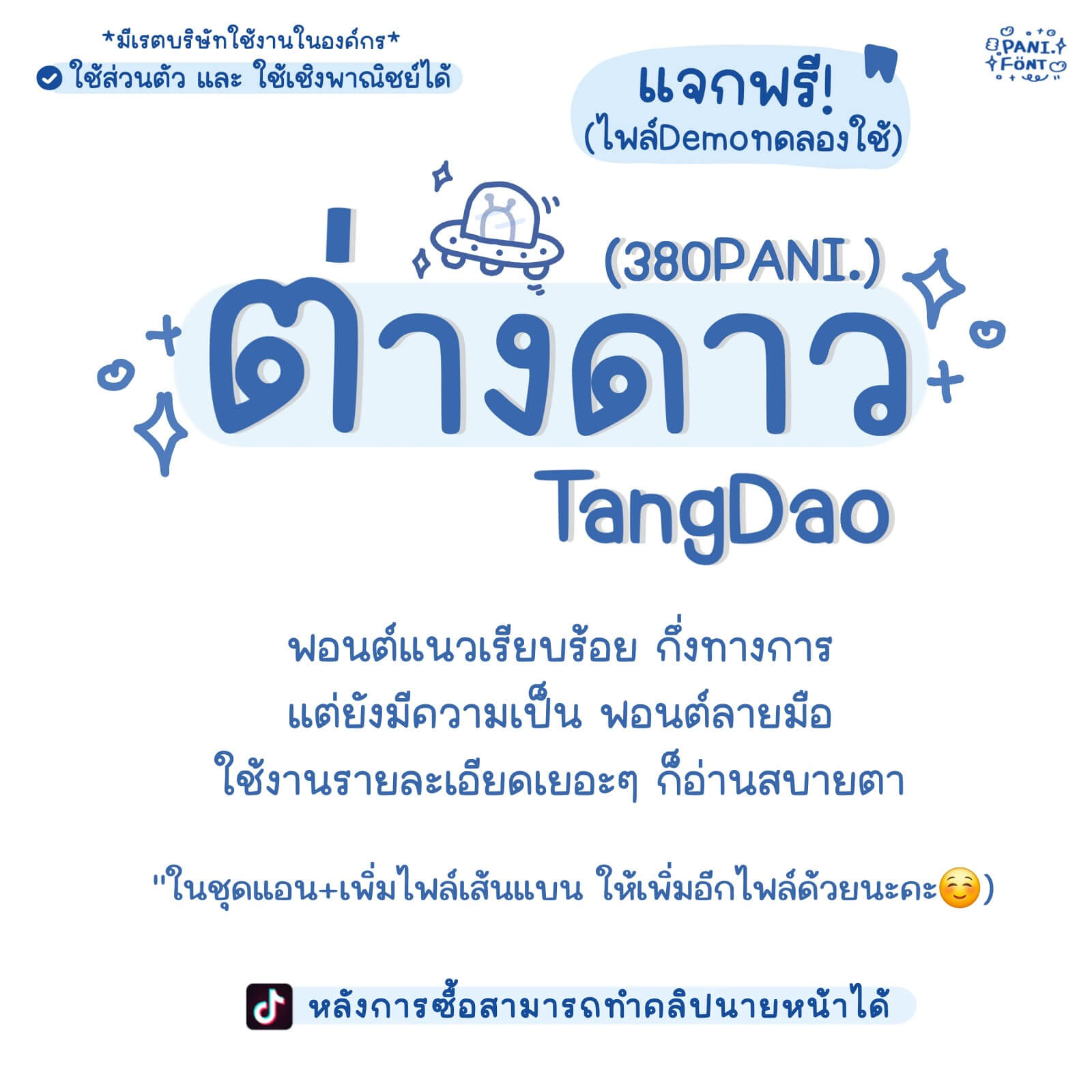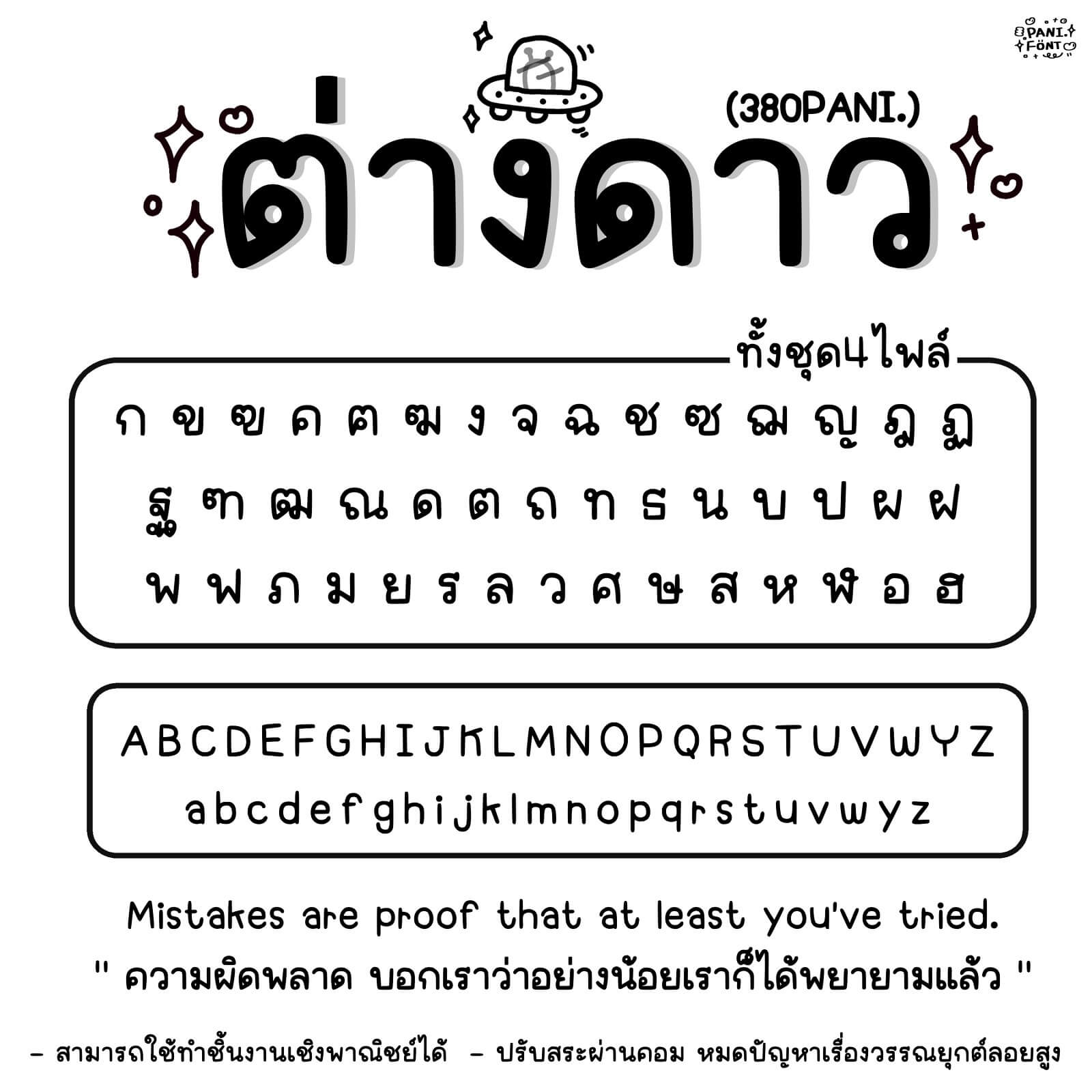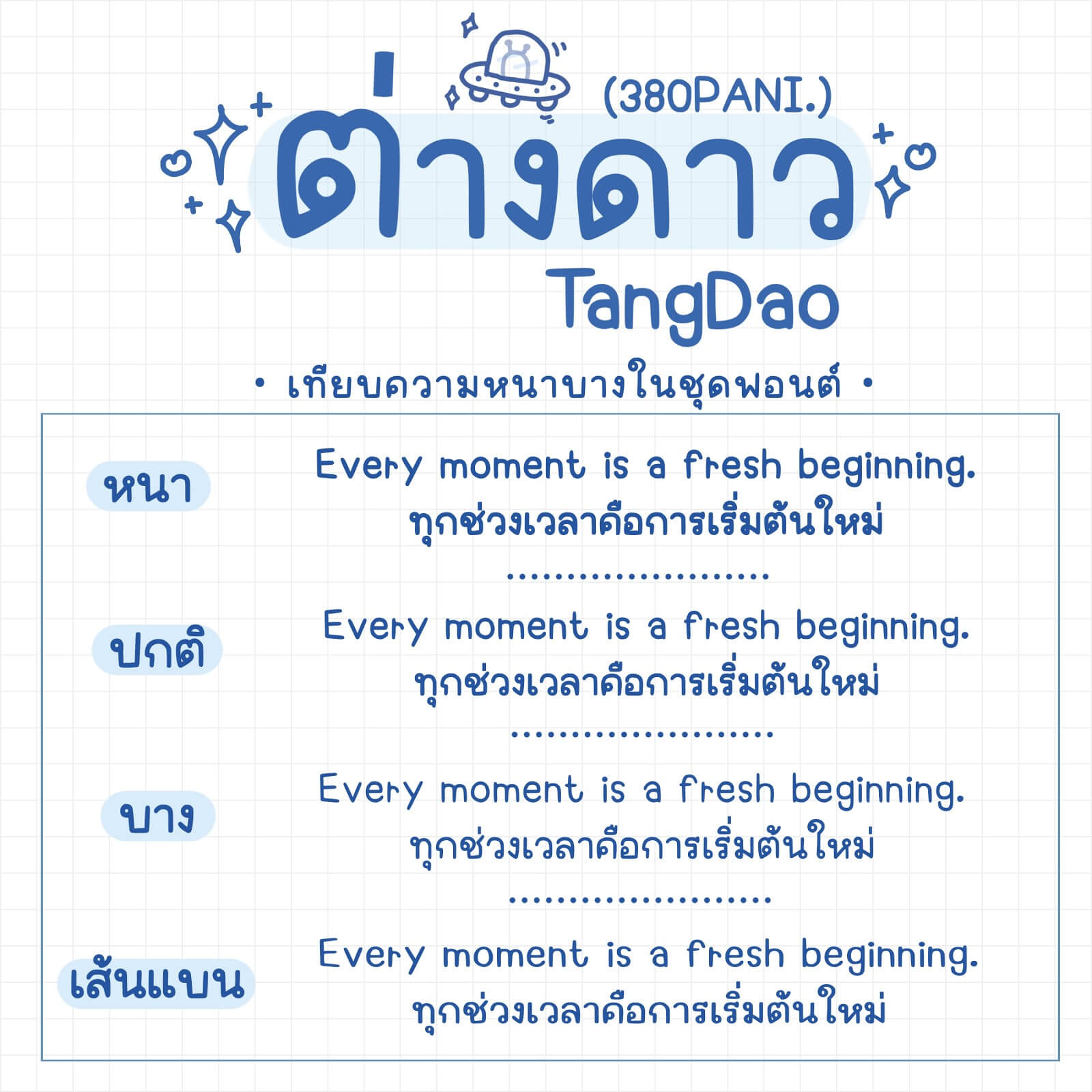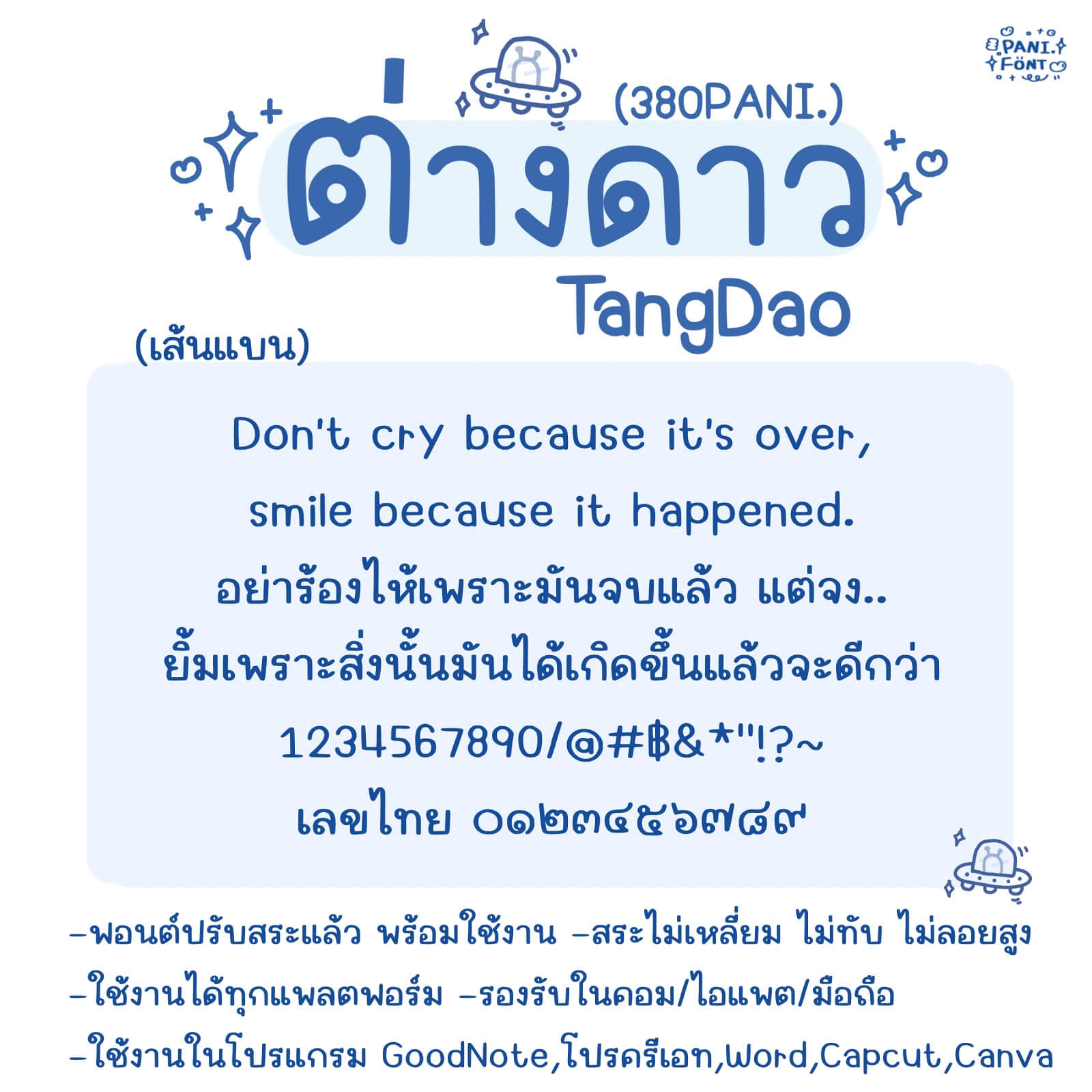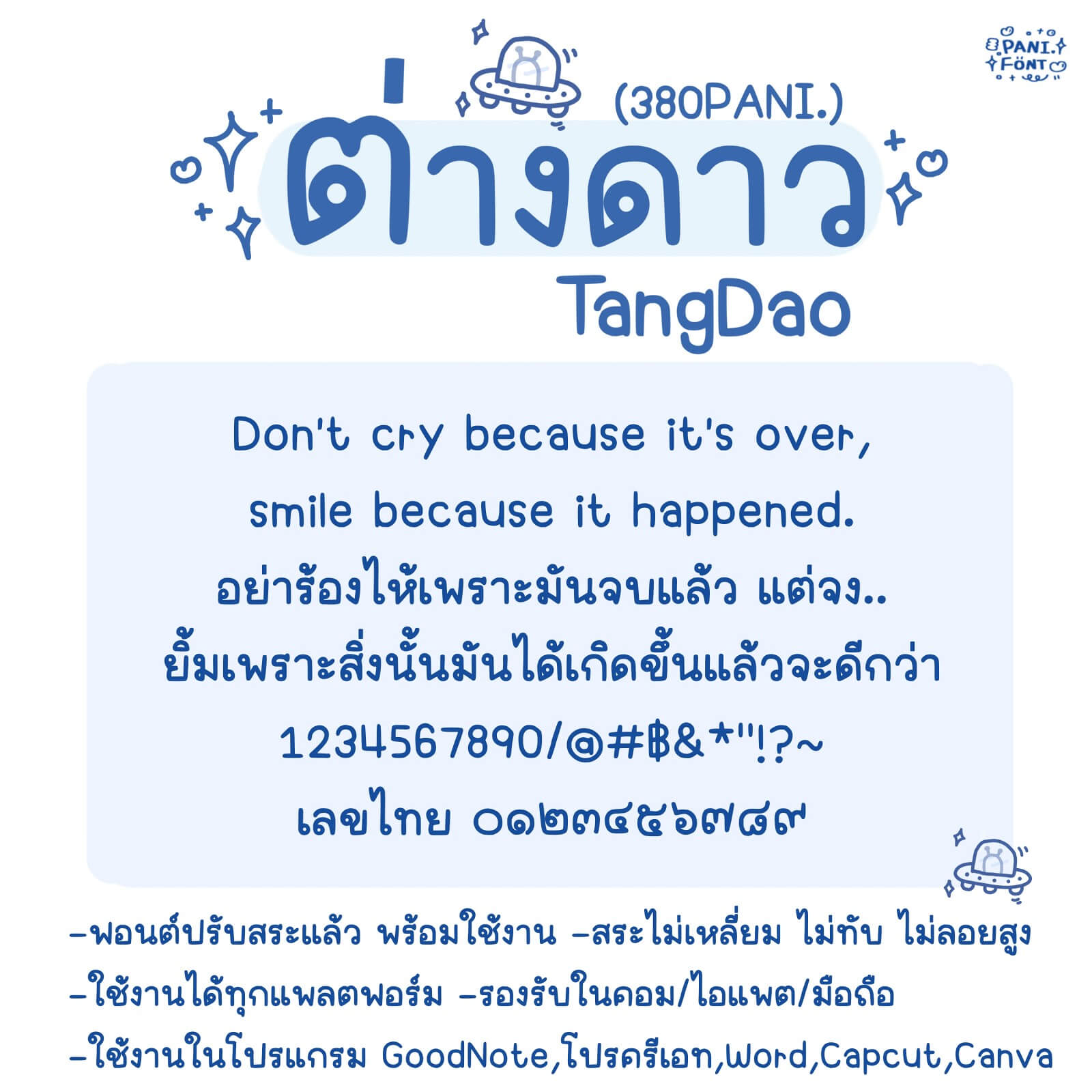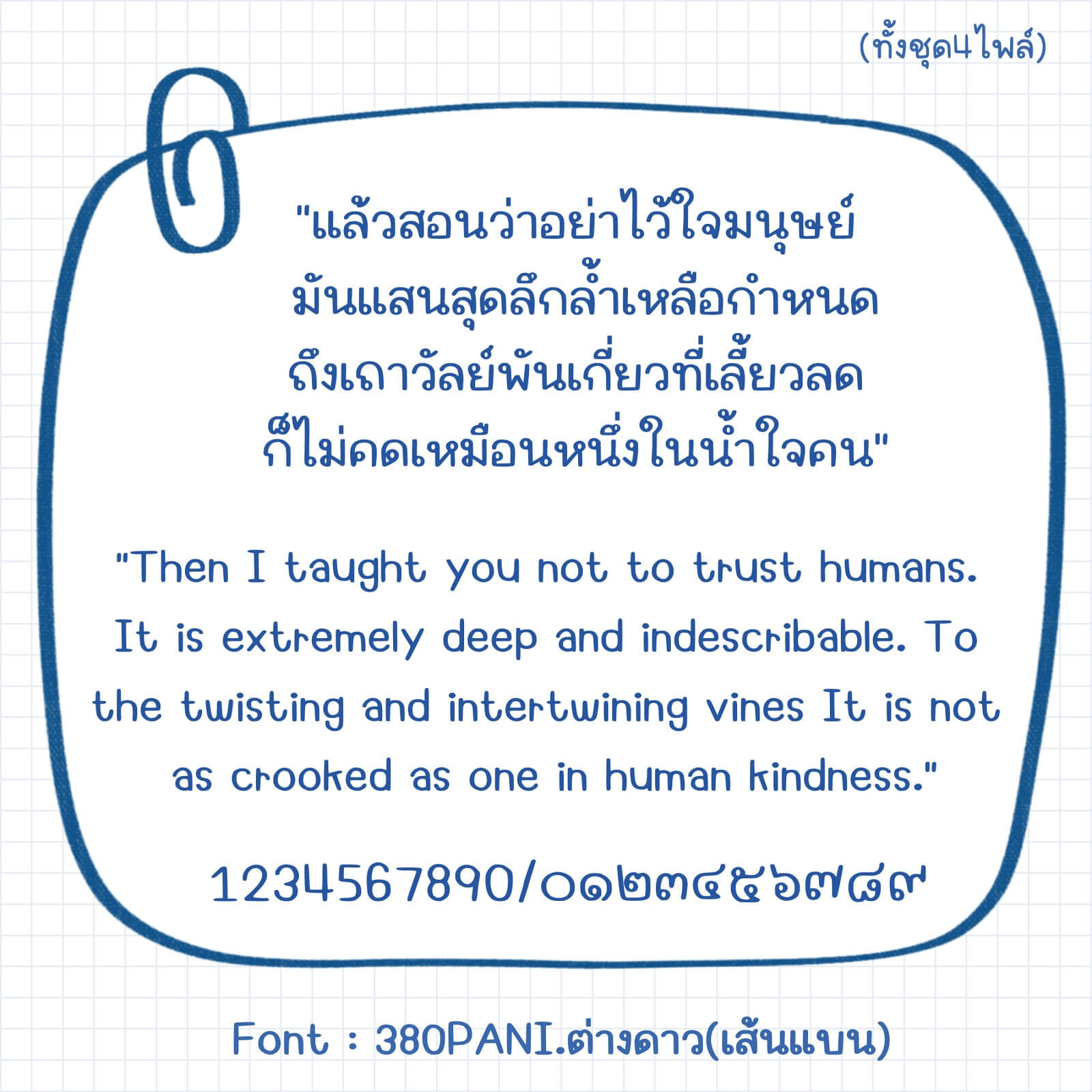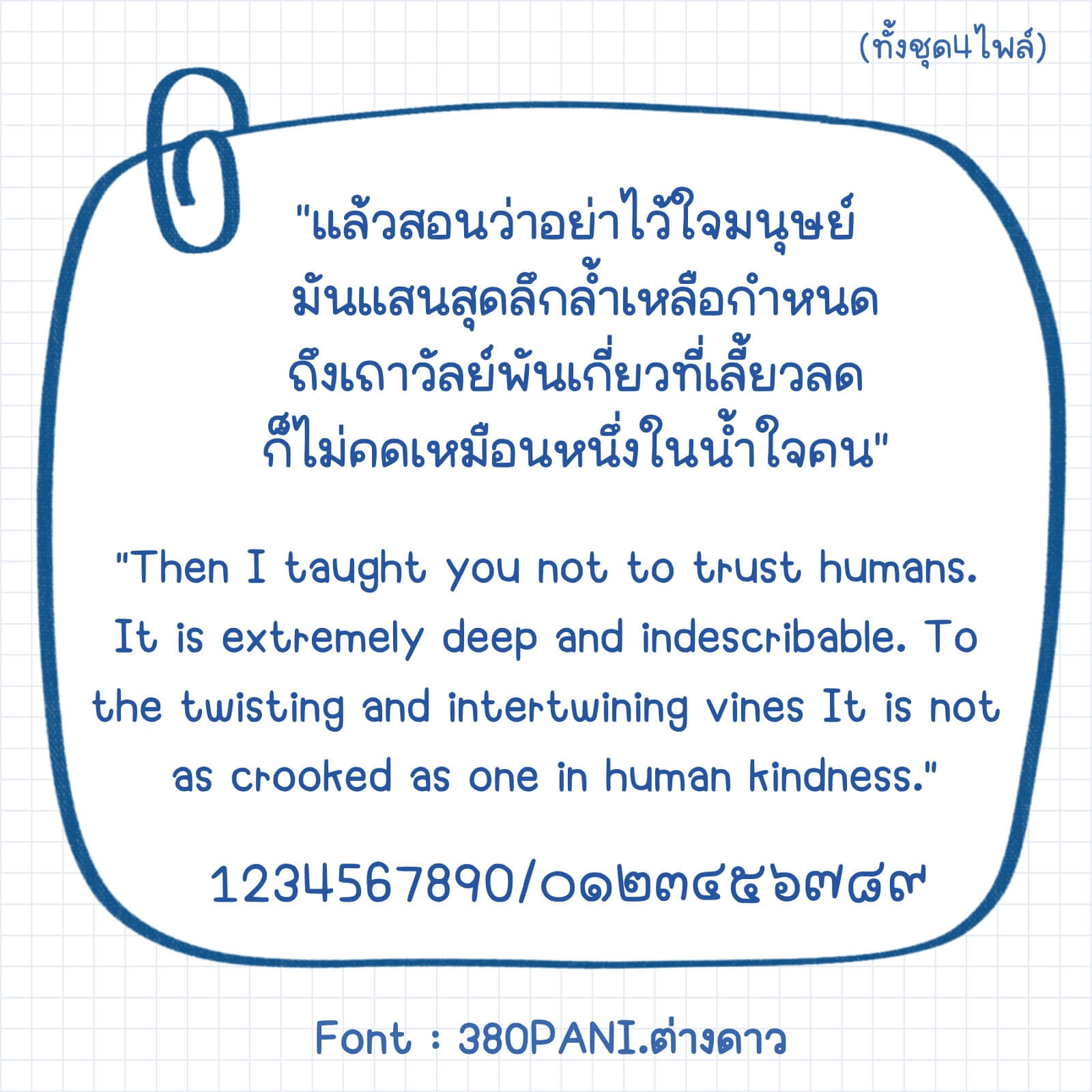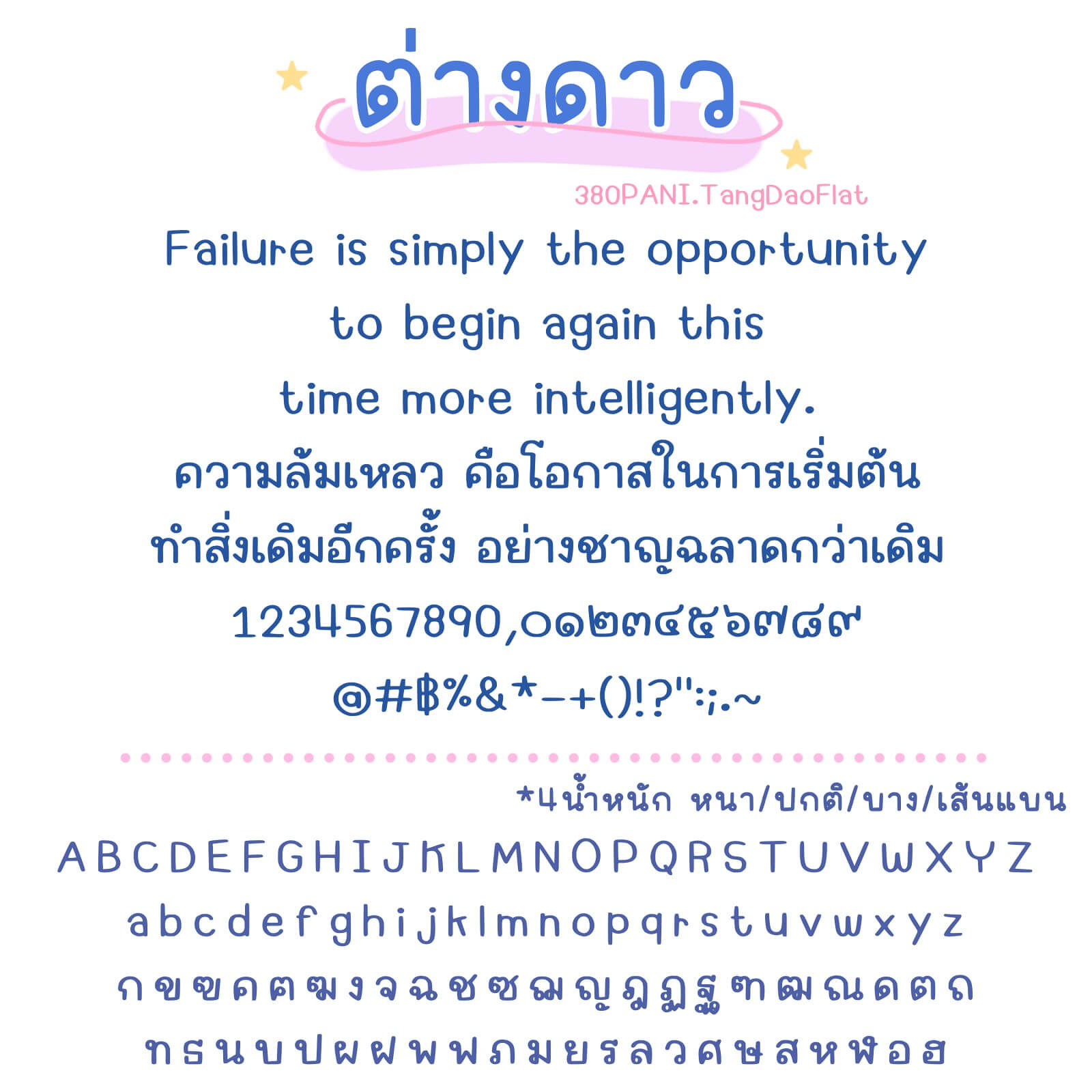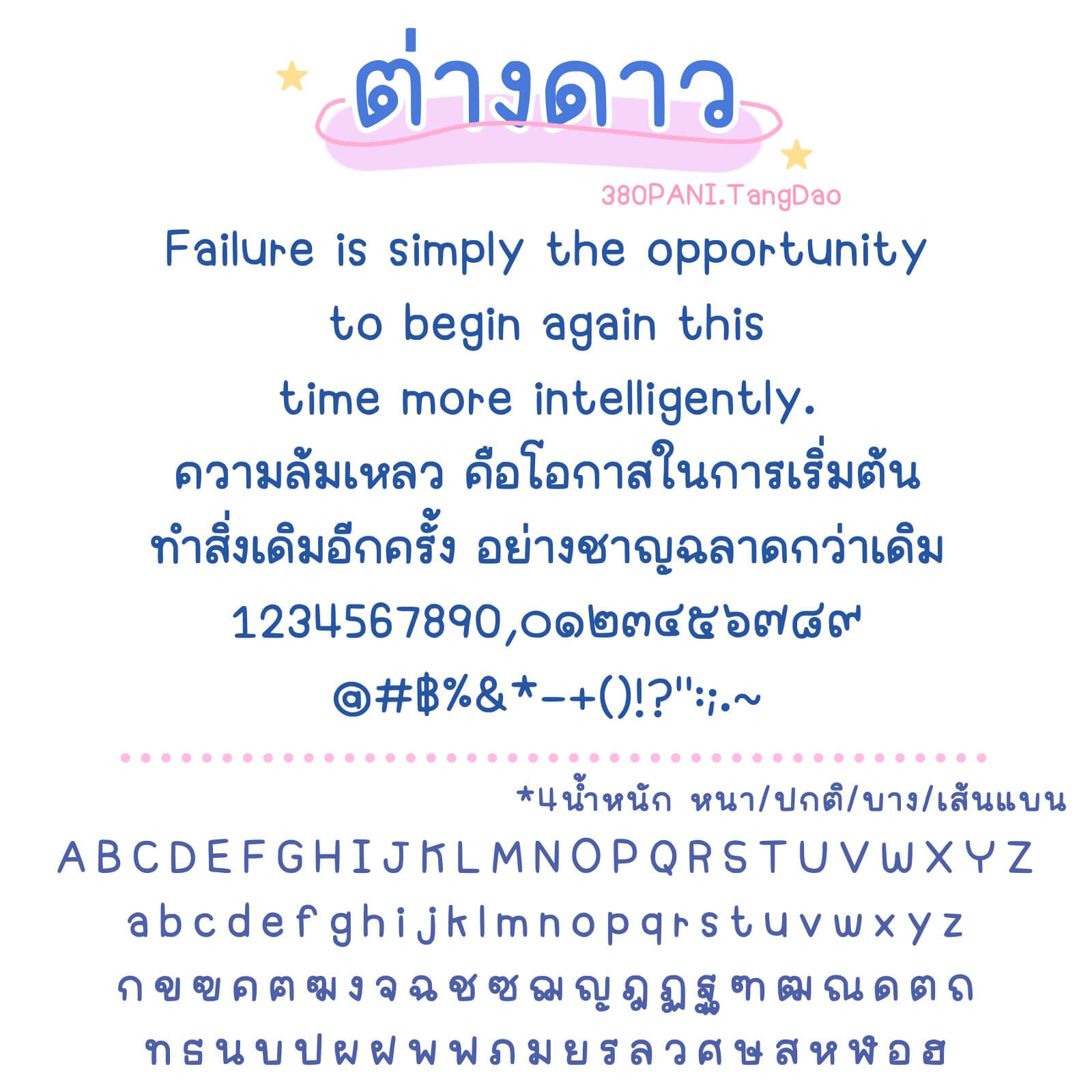
ฟอนต์ 380PANI.ต่างดาว – ฟอนต์แนวเรียบร้อย กึ่งทางการ แต่ยังคงมีความเป็นฟอนต์ลายมือ แอนทำเส้นแบน เพิ่มอีกไฟล์ในชุดให้ด้วยค่ะ
ฟอนต์มี 4 ไฟล์ – น้ำหนัก บาง ปกติ หนา เส้นแบน